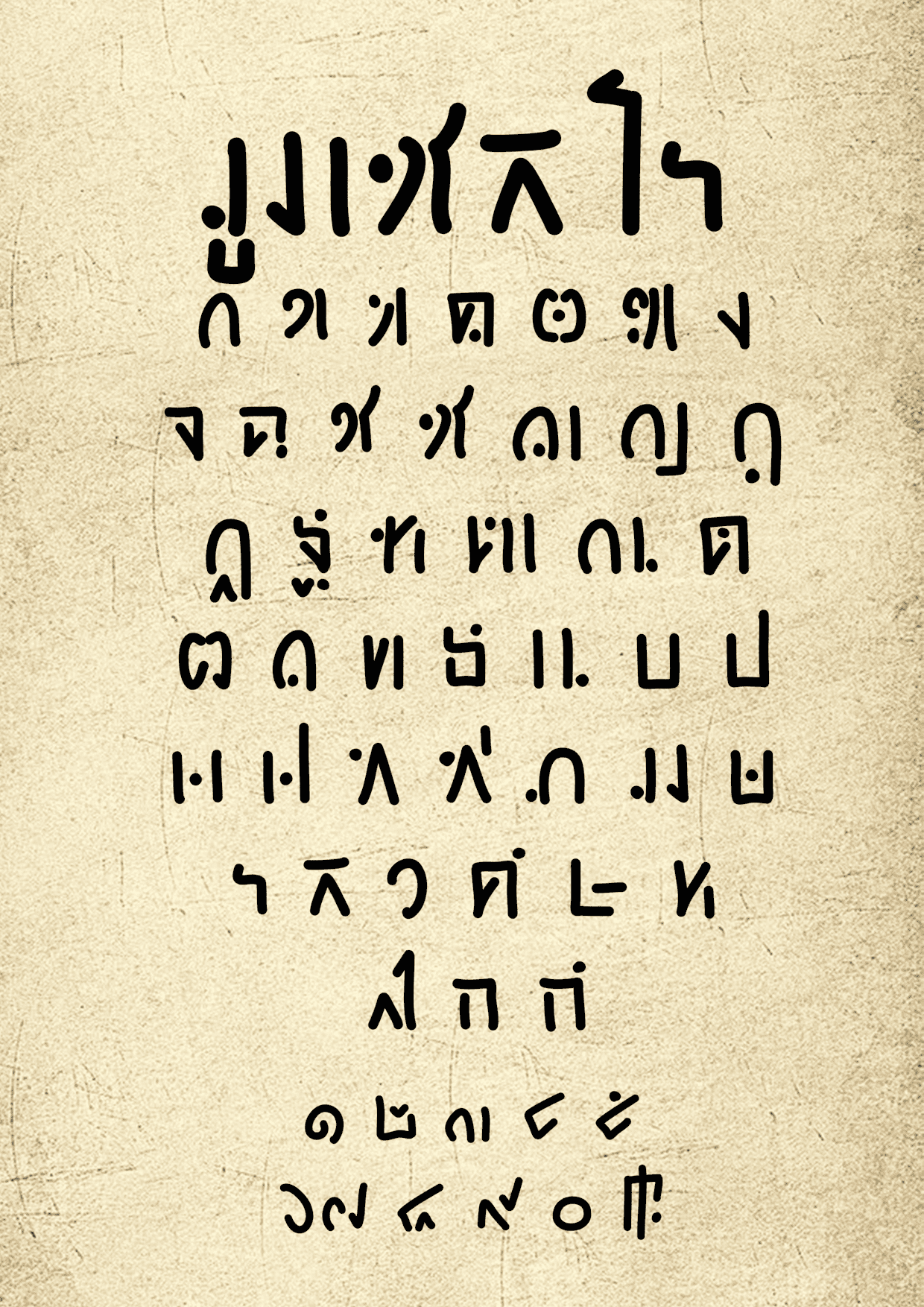
ฟอนต์ มูเซลโร muzelro
mulzeru
ฟอนต์ มูเซลโร muzelro
แก้สระแล้ว
แรงบัลใจมาจากความขี้เกียจเขียนอักษรรูนในภาพวาด
ตัวฟอนต์ออกแบบมาให้อ่านเหมือนจะได้แต่ไม่
ทำให้ตัวอักษรดูดีอย่างเดียวไม่ต้องให้คนอ่านได้